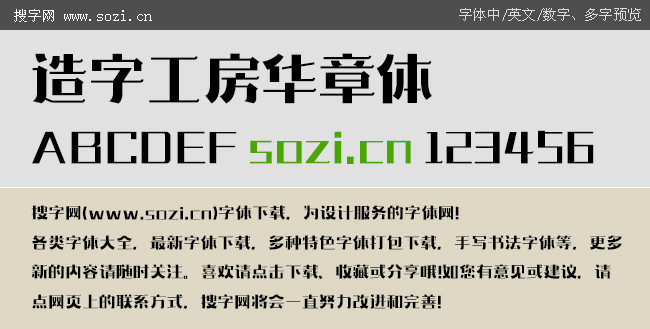
造字工房華章體
搜字網(wǎng)給大家提供一款造字工房華章體中文字體下載,造字工房華章體字形樸茂工穩(wěn),剛勁峻拔,結(jié)體方整勻稱,章法簡約嚴(yán)謹(jǐn),渾厚高古。筆畫上借鑒隸書筆意,汲取精華再設(shè)計,點畫精到,,疏密均衡,增省有度,有極強(qiáng)的視覺表現(xiàn)力。適用于大標(biāo)題、包裝設(shè)計、海報設(shè)計等應(yīng)用。(本字體為個人非商用版,如需要商用請聯(lián)系官方購買版權(quán))